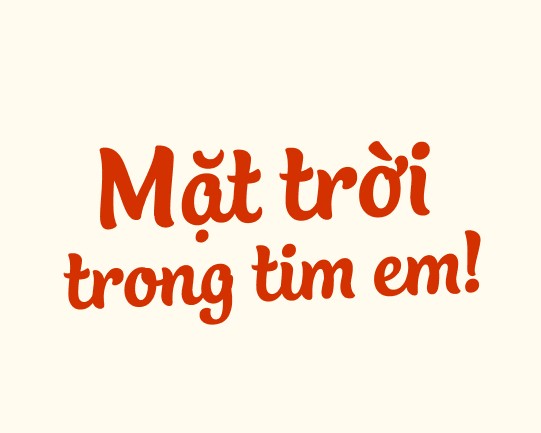
SVN-Bali Script là bộ font chữ viết tay mang đậm hơi thở của những chuyến du lịch và vẻ đẹp phóng khoáng của vùng nhiệt đới. Sự ra đời của font chữ svn-bali script Việt hóa cung cấp cho người làm sáng tạo một công cụ hiệu quả để thể hiện sự tự do, gần gũi trong các ấn phẩm truyền thông mà không gặp trở ngại về lỗi hiển thị tiếng Việt.
Sức hút từ phong cách tự nhiên của font chữ SVN-Bali Script Việt hóa
Nét chữ của SVN-Bali Script mô phỏng sinh động những vệt cọ quét đầy ngẫu hứng, tạo nên cảm giác thủ công và giàu tính nghệ thuật. Điểm đặc trưng của bộ font này nằm ở cấu trúc chữ có độ nghiêng nhẹ, kết hợp cùng các đường nét uốn lượn nhưng vẫn giữ được sự chắc chắn, vững chãi. Bản Việt hóa đã được xử lý bảng mã Unicode chuẩn, giúp các dấu thanh phối hợp hài hòa với thân chữ, duy trì vẻ đẹp hoang dại và tinh tế của bộ chữ gốc trong mọi bản thiết kế.
Bên cạnh yếu tố thẩm mỹ, SVN-Bali Script còn mang lại năng lượng tích cực và sự thư giãn cho người xem. Khi được ứng dụng vào văn bản, font chữ này giúp xóa bỏ sự khô cứng thường thấy, mang lại nhịp điệu sinh động cho các tiêu đề và slogan. Đây là lựa chọn phù hợp cho những ai muốn tìm kiếm sự khác biệt, đề cao tính cá nhân và phong cách sống tự tại cho thương hiệu hoặc dự án kiến trúc của mình.
| Phân loại phong cách | Brush Script / Summer / Tropical Style |
| Mục đích phù hợp | Tiêu đề, Bảng hiệu, Poster, Branding |
Gợi ý phối hợp: SVN-Bali Script có cá tính mạnh và nét chữ khá dày. Để đạt được sự cân bằng về thị giác, bạn nên phối hợp font này cùng một font không chân (Sans-serif) tối giản cho phần nội dung mô tả chi tiết, giúp thông tin chính luôn nổi bật và rõ ràng.
03 Ứng dụng font SVN-Bali Script vào thực tế trang trí công trình
Nhờ vẻ ngoài giàu tính thẩm mỹ và đậm chất “tropical”, bộ font này mang lại giá trị cao khi được đưa vào thực tế quảng bá và trang trí không gian:
- Bảng nhận diện cho Homestay & Cafe: Những nét chữ phóng khoáng của SVN-Bali Script rất ăn ý khi xuất hiện trên biển hiệu gỗ, mây tre lá hoặc alu phủ màu tại các khu nghỉ dưỡng, homestay lắp ghép mang phong cách tự nhiên.
- Thiết kế Menu và Voucher: Sử dụng font chữ này cho tiêu đề chính giúp khơi gợi cảm hứng về một không gian thư giãn, vui vẻ, dễ dàng tạo thiện cảm với khách hàng ngay từ cái nhìn đầu tiên.
- Trang trí không gian nội thất: Bạn có thể dùng font này để cắt chữ nổi hoặc in decal trang trí tường tại sảnh chờ văn phòng container nhằm tạo điểm nhấn đầy nghệ thuật và năng động cho không gian làm việc.
03 Lưu ý khi trình bày bố cục với font chữ SVN-Bali Script Việt hóa
Để khai thác hiệu quả vẻ đẹp của dòng font brush script này mà không làm rối mắt người đọc, người thiết kế nên lưu tâm một số điểm sau:
- Tránh viết hoa toàn bộ ký tự: Đặc trưng của SVN-Bali Script là nét nối mượt mà giữa các chữ thường. Việc sử dụng toàn bộ chữ in hoa sẽ làm mất đi nhịp điệu tự nhiên và gây khó khăn cho việc nhận diện mặt chữ.
- Kiểm soát khoảng cách dòng: Do một số nét chữ có xu hướng vươn cao, bạn nên để khoảng cách dòng thoáng một chút để các dấu tiếng Việt không bị chồng chéo lên nhau.
- Lựa chọn màu sắc rực rỡ: Font phong cách nhiệt đới phát huy hiệu quả thị giác cao khi phối cùng các tông màu nóng, màu xanh lá hoặc màu gỗ sáng để tôn vinh tinh thần tự do của bộ chữ.